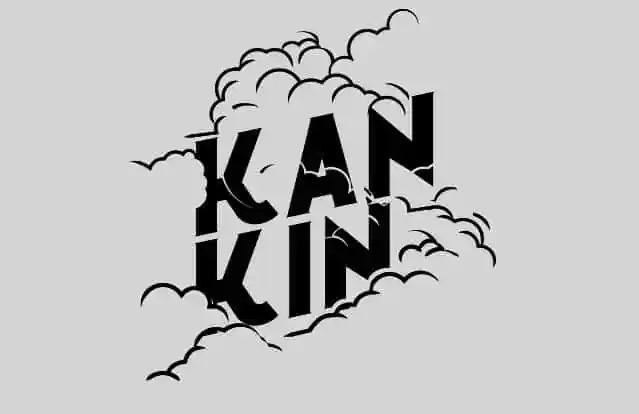
Kánkin Typeface – Fonte Grátis
Kánkin Typeface
Introduzimos uma nova família de fontes tipo sans serif. Introducing Kánkin Typeface! Cona é um projeto desenvolvido por Alex Frukta e compartilhado com o público. KanKin é a última adição à coleção dos estilos de fonte sem serif, criada pelo designer Alexey Frukta. Lançado como uma oferta gratuita, KanKin traz um toque único ao estilo clássico que se adapta perfeitamente às linhas modernas e curvilíneas da fonte. Esta fonte é extremamente versátil e adequada para diversos tipos de design gráfico, incluindo web, impressão, gráficos em movimento, além de ser ideal para t-shirts e outros itens como posters, logomarcas e arte digital. KanKin não só traz uma nova opção para designers que buscam um estilo contemporâneo e sofisticado, mas também oferece flexibilidade na criação de designs retro ou modernos. Com sua estrutura fluida e curvilínea, a Kánkin Typeface é ideal para estilos diversos que precisam de uma fonte sem serif. Este novo projeto do designer Alexey Frukta traz o melhor das fontes clássicas ao design moderno, fazendo com que KanKin seja uma escolha perfeita tanto para projetos tradicionais quanto para os mais contemporâneos.